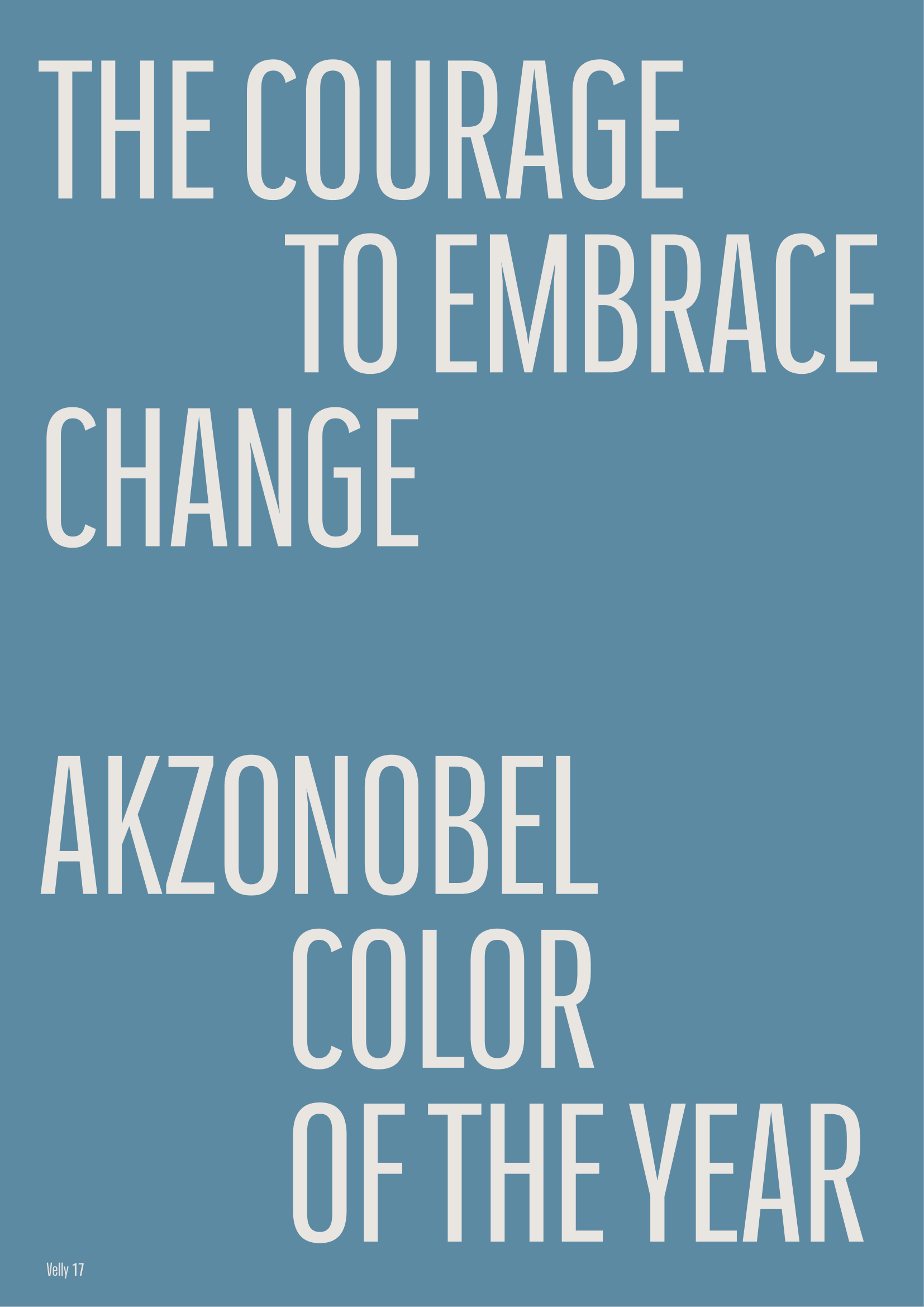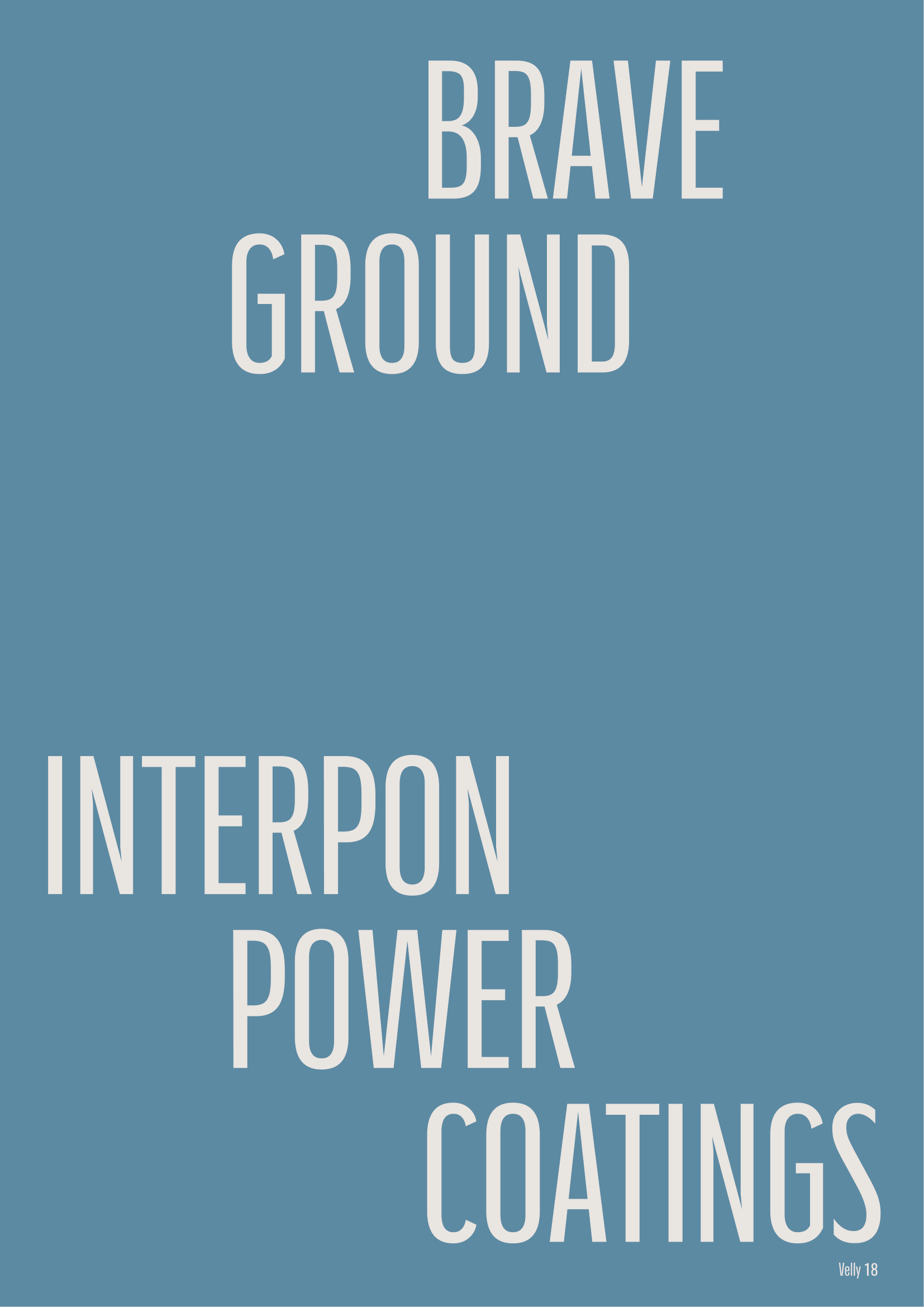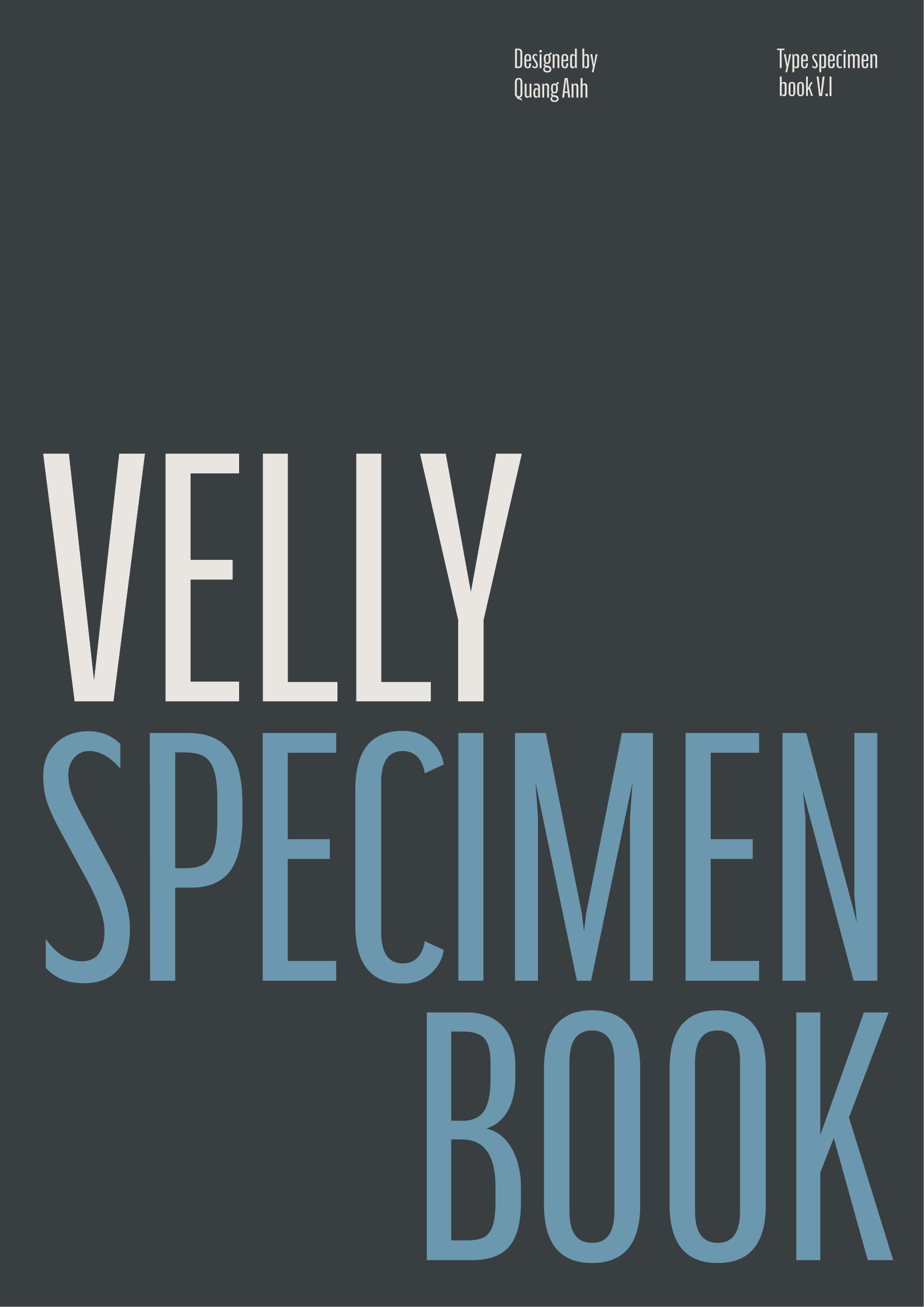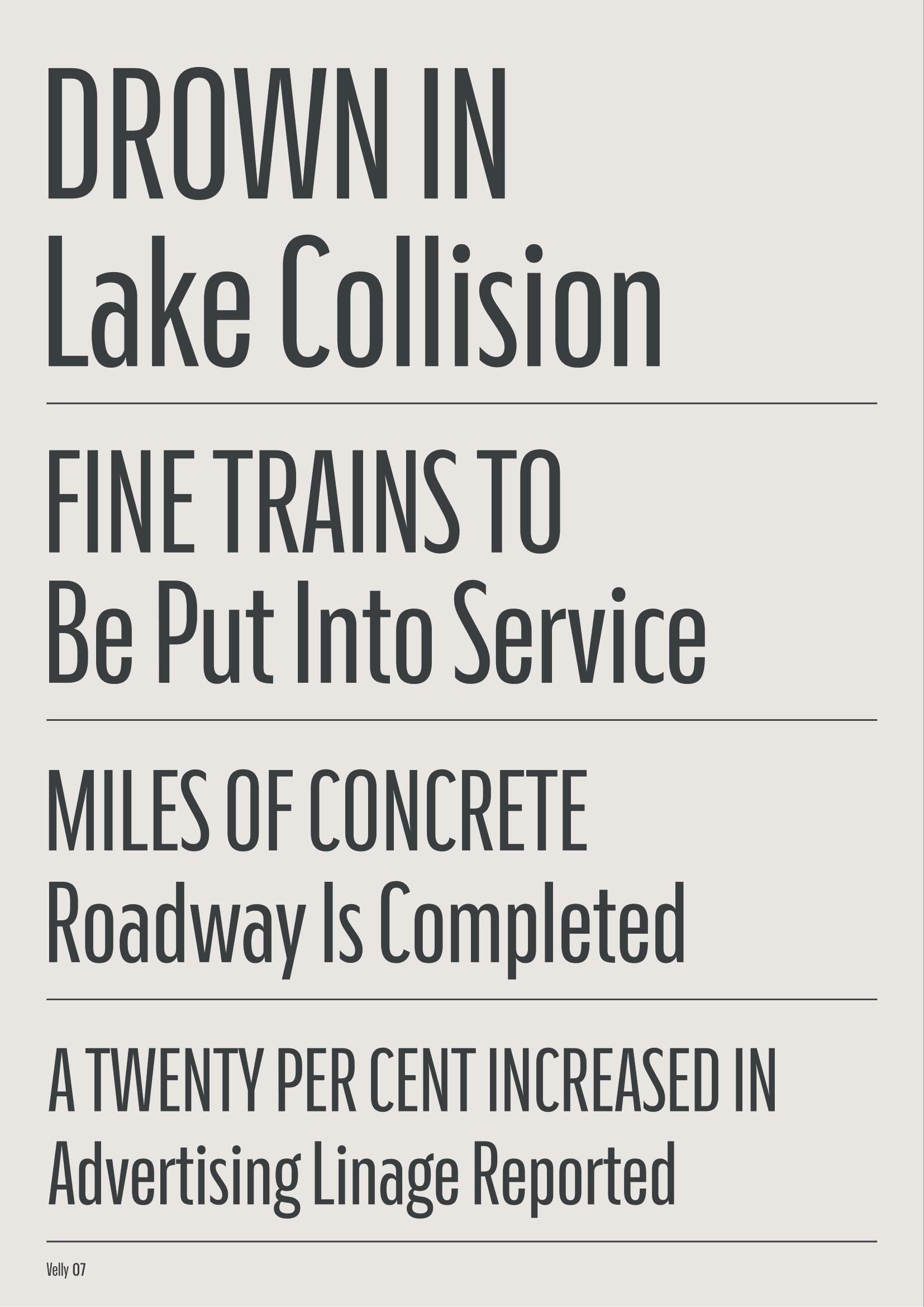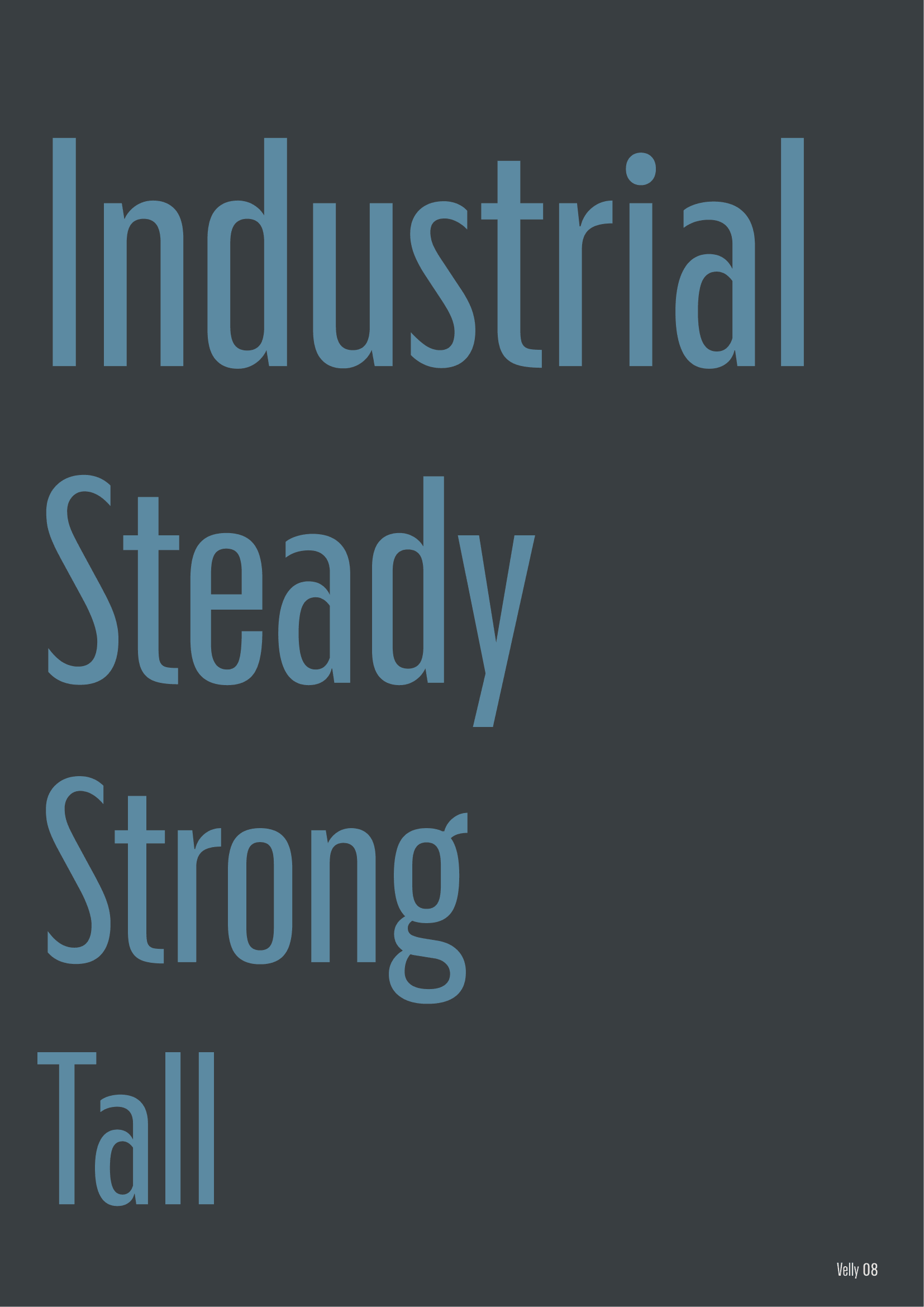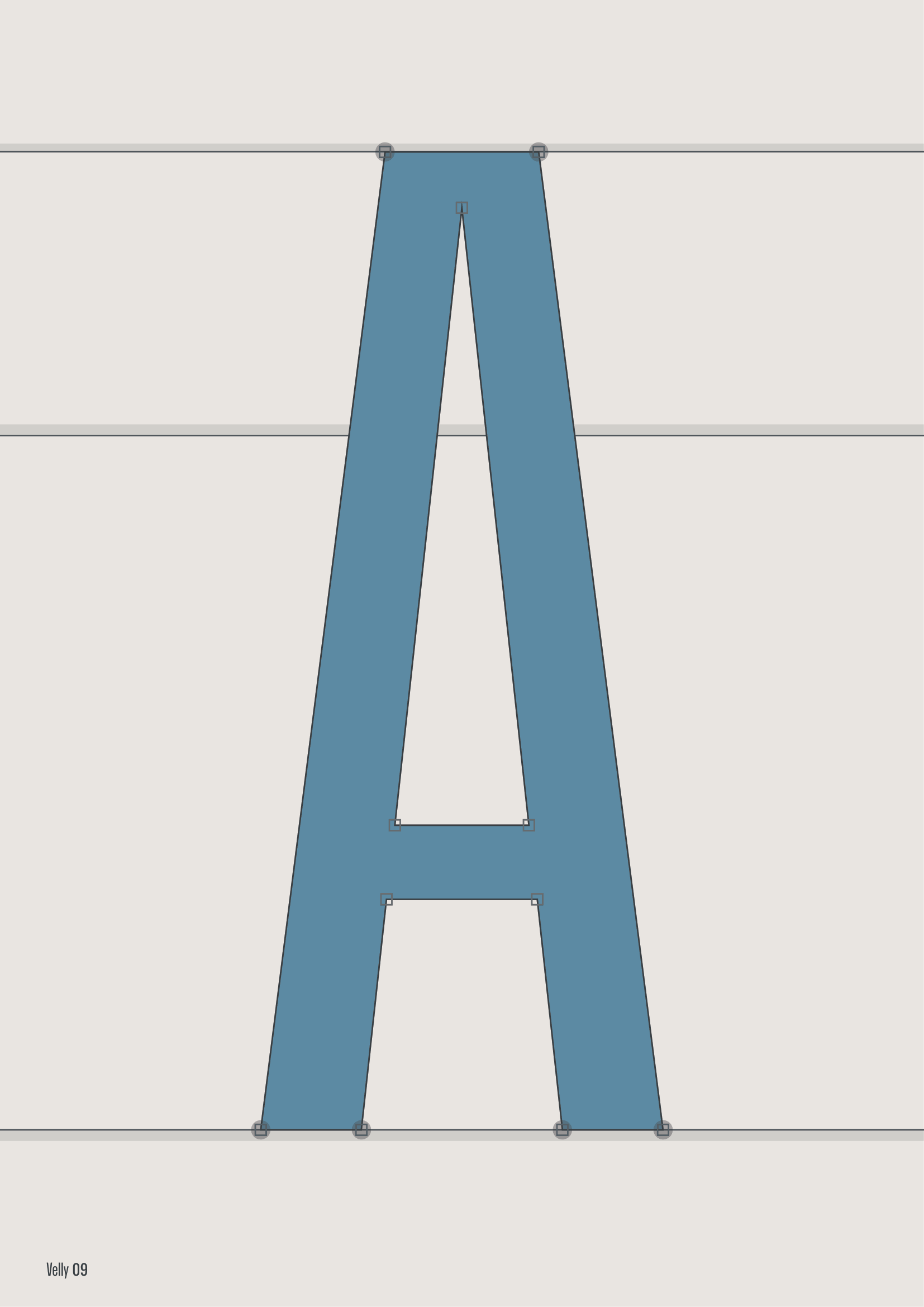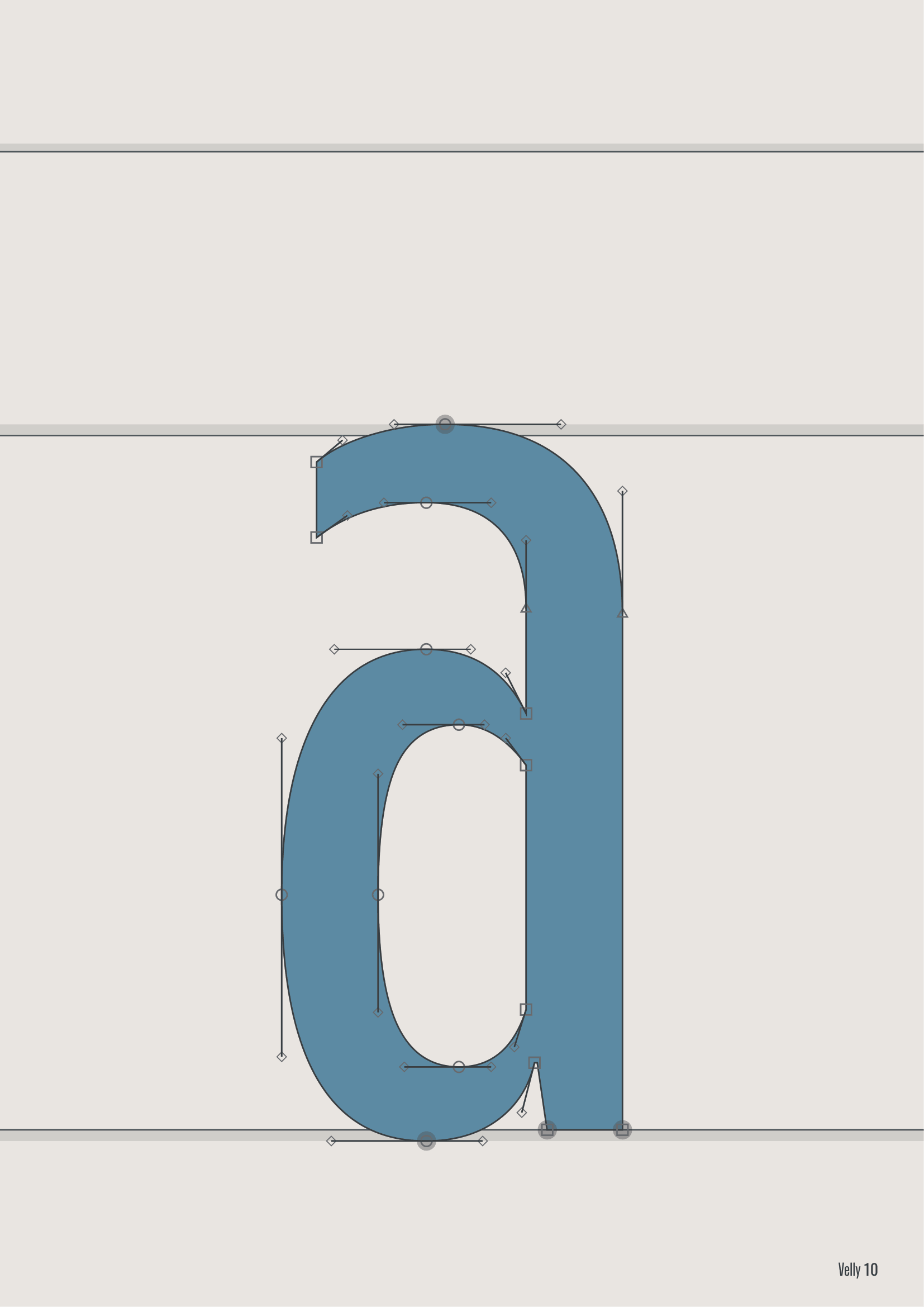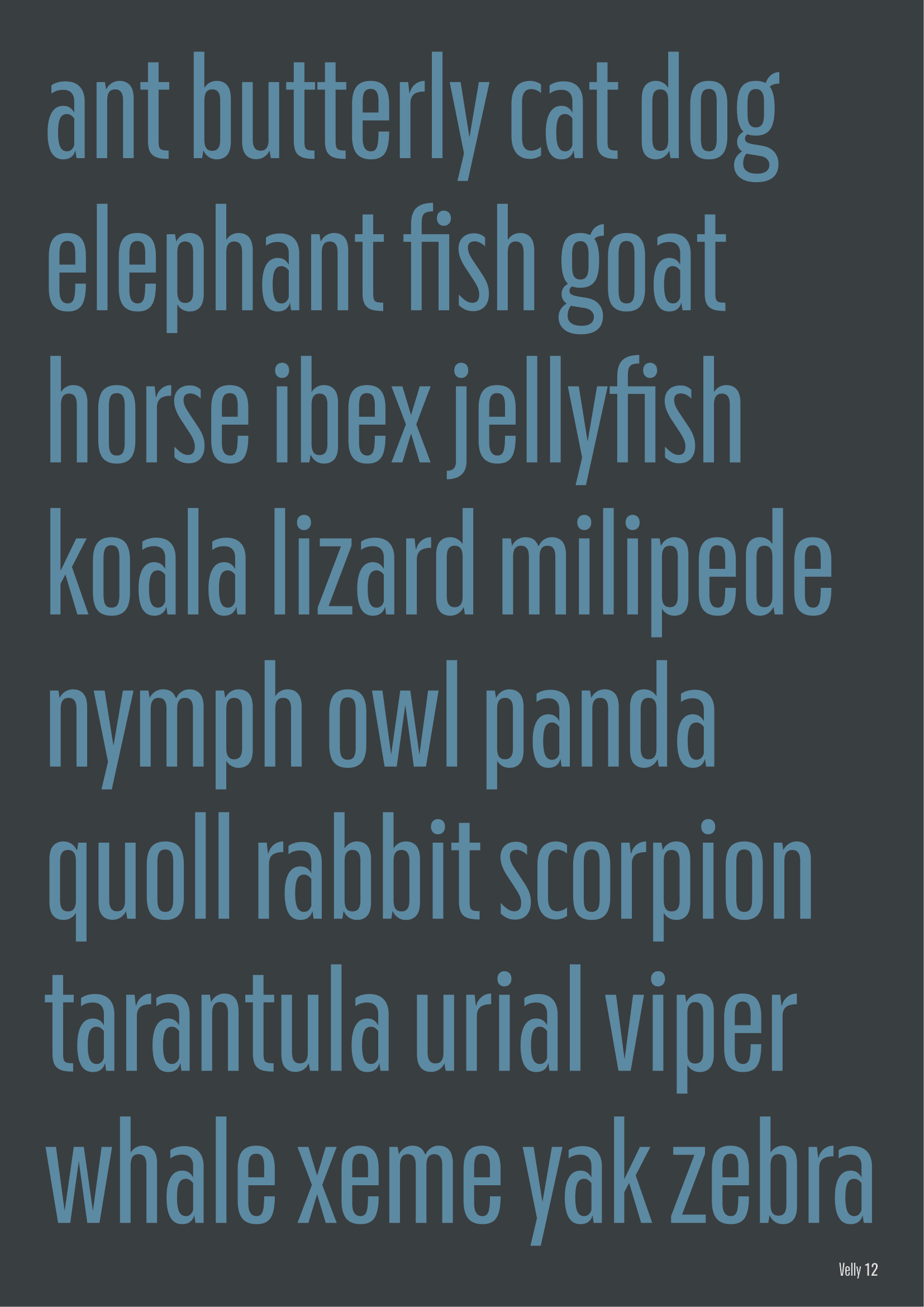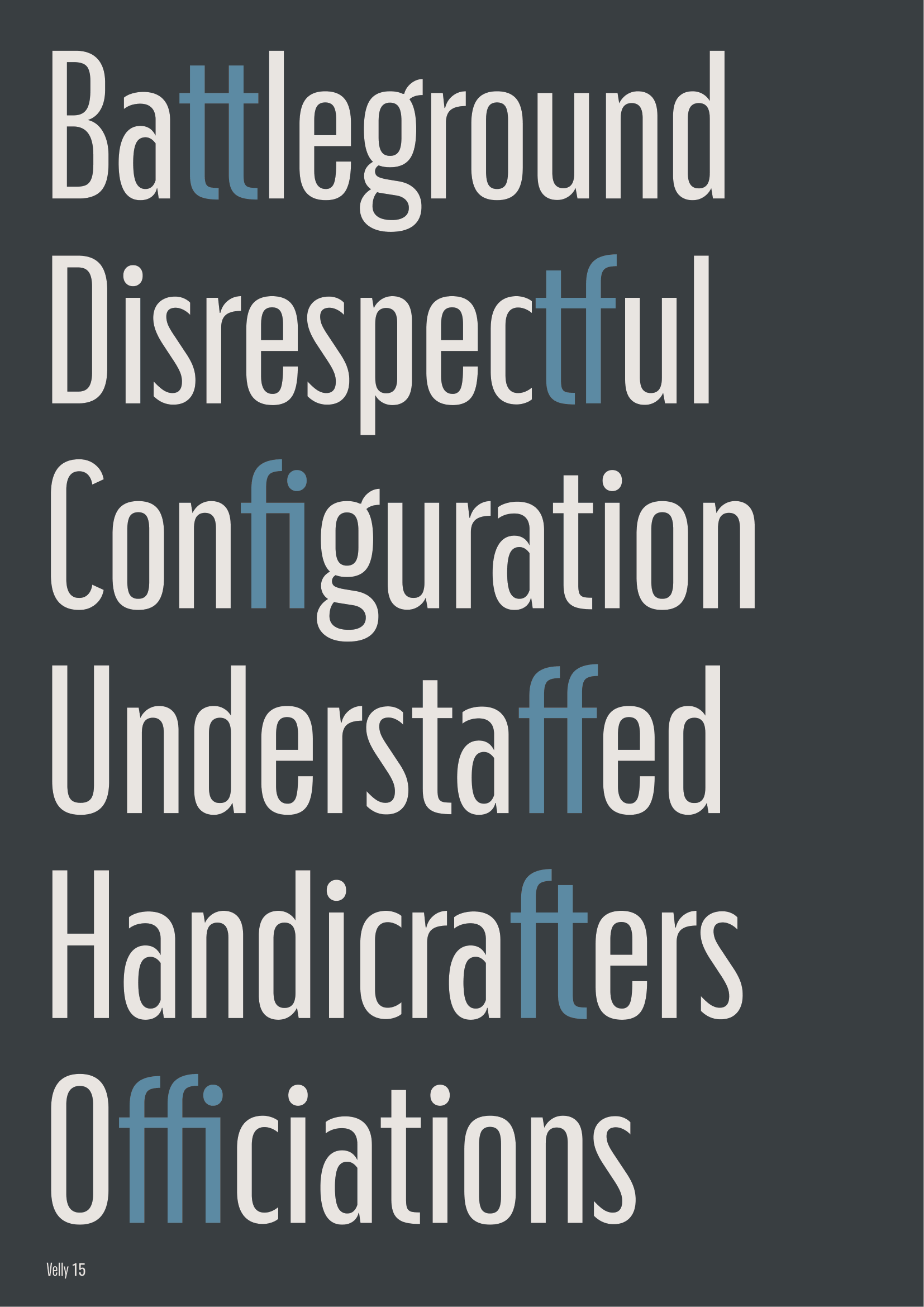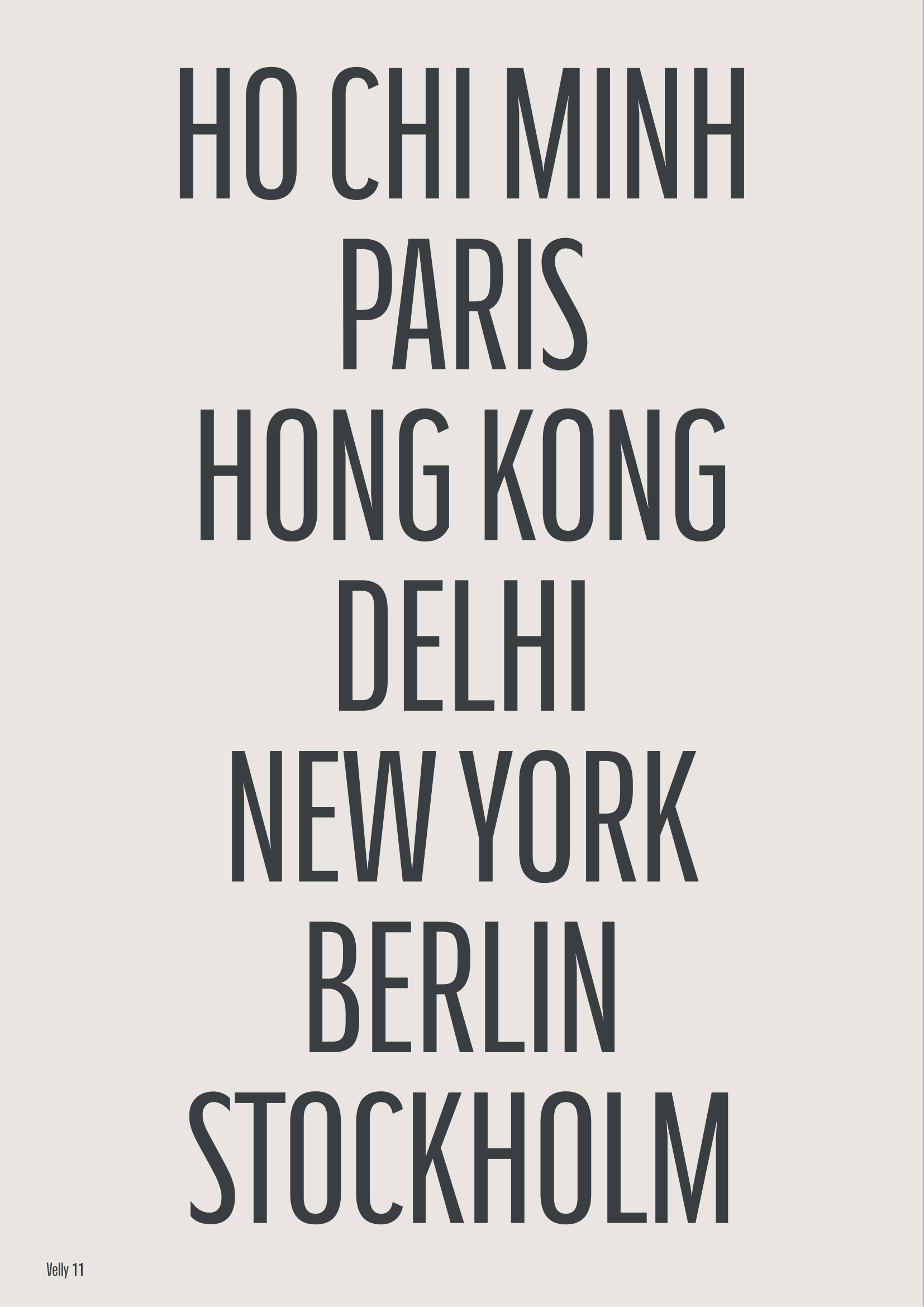
QA Velly
Về QA Velly: Velly là phông phục dựng từ kiểu chữ Ludlow Tempo Condensed, được thiết kế bởi R. Hunter Middleton, và được kết hợp với DIN của Albert Jan Pool. Khác với Futura, Velly là một kiểu chữ hình học dạng condensed, tuân theo những tỷ lệ hình học nghiêm ngặt giống như các kiểu chữ Đức, trong đó các nét chữ được tạo theo góc 45 hoặc 90 độ để hình thành các khối hình chữ nhật. Tính nhất quán này tạo cảm giác công nghiệp. Velly mạnh mẽ, vững chắc và cao ráo.
Geometric San Serif
Display
Quang Anh
QA Velly
INDUSTRIAL
QA Velly
Geometrical
QA Velly
Courageous
QA Velly
Strict Mechanic
QA Velly
Velly is a reconstruction of the Ludlow Tempo Condensed typeface designed by R. Hunter Middleton and blended with DIN by Albert Jan Pool.
QA Velly
Velly retains the same horizontal proportions and typeface as Tempo. Still it has been increased vertically and the letters are now shaped like a rectangular block similar to DIN to serve for the title and characterization especially for use in tight spaces.